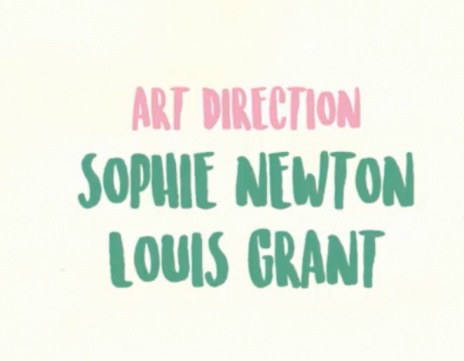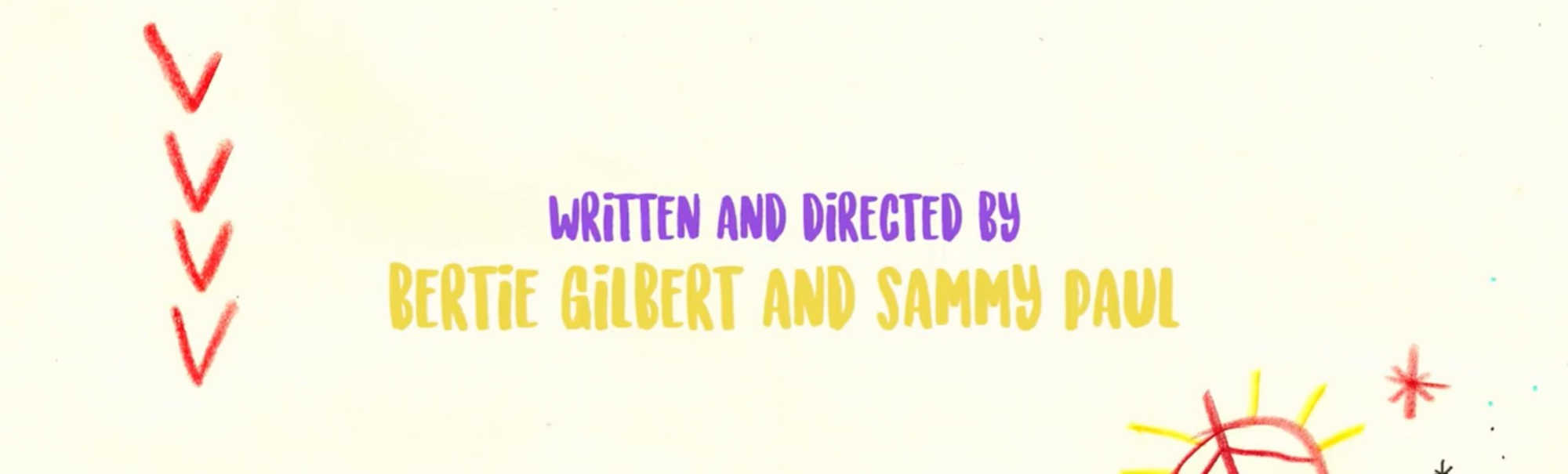
Suche Schriftart aus dem Abspann des Kurzfilms "Playground" (2017)
im Kurzfilm "Playground" von Bertie Gilbert und Sammy Paul aus dem Jahre 2017 wird eine Schreibschrift verwendet, Gerät am ehesten wahrscheinlich Marker. Ich bin mir nicht sicher, ob diese extra für den Film designed wurde oder ob es eine etablierte Schriftart ist, deswegen brauche ich Hilfe bei der Identifiaktion. (Nur Name/ Designer:in reicht)
Im Anhang zwei Screenshots des Youtube-Videos (https://www.youtube.com/watch?v=EGsP4T9HDxc&t=3s), die die gesuchte Schriftart zeigen.